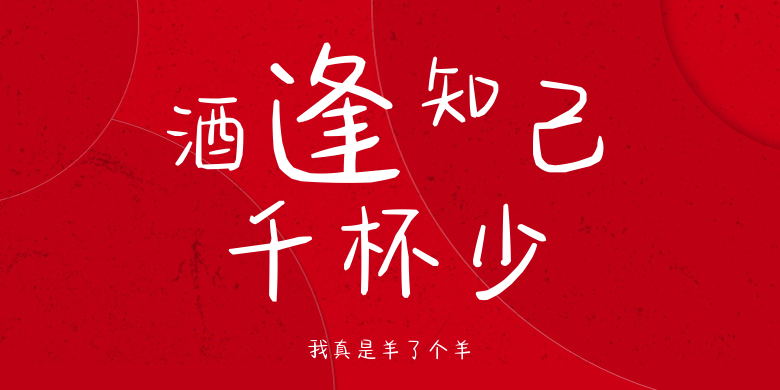
我真是羊了个羊
我真是羊了个羊,这款字体结构工整、笔画清晰,兼顾美观与易读性,适用于标题、正文、海报、包装、LOGO 等多种场景。字形优雅稳定,风格百搭耐看,适配日常排版与创意设计,让文字呈现更舒适、更具质感。我真是羊了个羊一笔一画,皆是细节,以均衡的比例、流畅的线条打造舒适视觉体验,字形端正大气,风格简约现代。无论是商业设计、品牌宣传还是日常排版,都能轻松驾驭,让文字更有格调与力量。我真是羊了个羊字体下载。